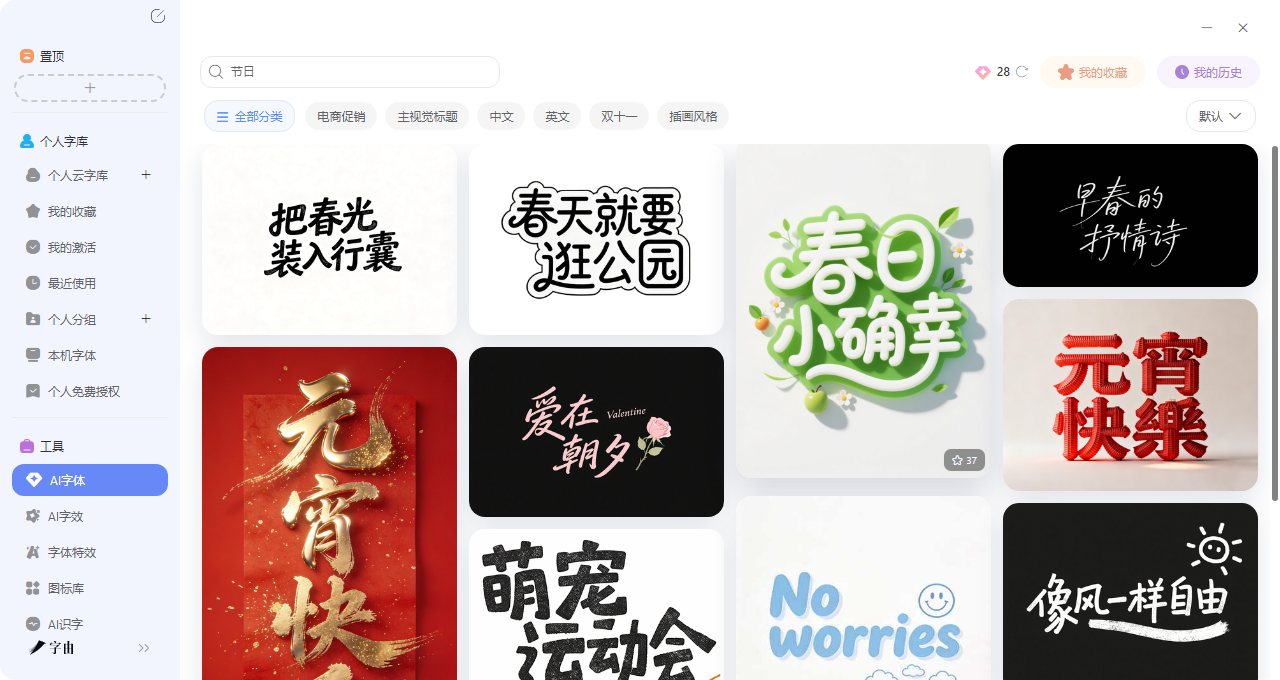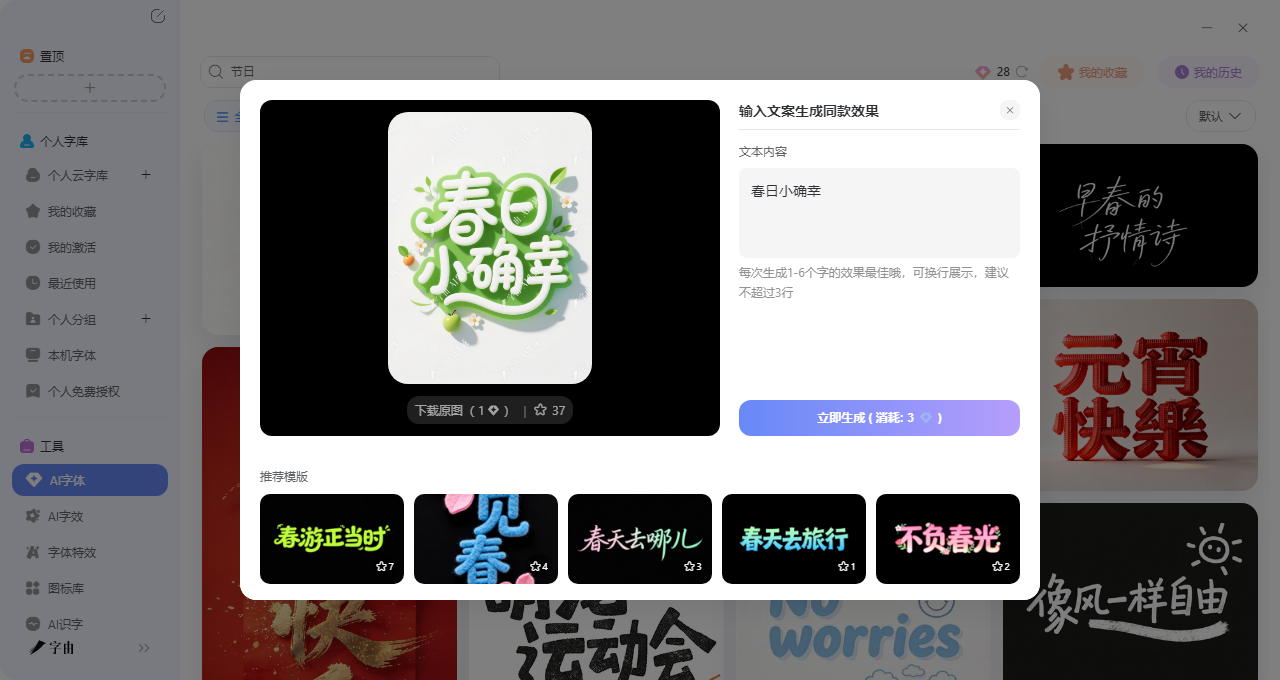
短视频花字自动生成,30秒出效果,剪辑效率翻倍
现在短视频可谓是深入到了我们生活的方方面面,但是所有的优秀的短视频背后肯定都离不开一位优秀的剪辑和封面设计师,温馨的画面加上手写感的文字,酷炫的转场闪过带特效的标题……这些花字就像视频的“弹幕”,能够把情绪和重点精准地带给观众。如果你要问我怎么才能快速地做出一个优秀的短视频花字呢?那我会告诉你只需要在短视频花字自动生成工具里输入文字、选个风格,一键就能生成带特效的动效花字。今天我就筛选了4 个亲测好用的工具,从国产神器字由到国外专业平台,每个都能帮你快速搞定花字。需要的直接收藏,以后做视频不用再愁花字。
你有没有发现,那些爆款短视频里的花字,往往不只是单纯的文字,而是带着效果的艺术字——要么是弹跳入场,要么是渐隐渐显,要么是抖动闪烁。这种效果以前只能在剪辑软件里一帧一帧地做,现在字由的AI字体功能直接把它们做成了模板。更关键的是,你不需要懂动画,也不需要调参数,选个模板,填上文字,点一下,就能拿到带特效的动态花字。接下来我会详细说明如何制作:
第一步:进入AI字体页面后,在搜索框里输入“春日”“节日”“生活”“动态”等关键词,系统会自动筛选出所有适合做花字的模板。
第二步:选一个喜欢的花字模板,下面是推荐的一些模板样式:
- 文艺清新类:“春日”“把春光装入行囊”这种,适合vlog、旅行
- 活泼可爱类:“春天就要逛公园”“萌宠”这种,适合亲子、萌宠、美食
- 洒脱自由类:“像风一样自由”这种,适合运动、公路旅行
- 幸福治愈类:“小确幸”“快樂”这种,适合日常记录、情感短片
每个模板都有预览图,你可以先看效果再决定,点进去还能看到更多细节。选一个和你的视频风格搭的,如果拿不准,可以多试几个。
第三步:点击选中的模板,进入编辑页面。在输入框里填你想生成的花字内容,比如“春日限定”“周末愉快”“今日份快乐”。注意:最好和模板的字数保持一致。
第四步:确认文案后,点“立即生成”,等20-30秒左右就能拿到图。下载时有两个选项:带背景的可以直接用,透明背景的更方便后期排版。直接保存PNG格式,就能拖进剪映、PR等剪辑软件里直接叠加使用。
但是其实字由的AI模板库要比你想象得丰富得多,它不是只有“花字”这个分类,你在“春日”“节日”“生活”里翻到的模板,稍微改一下文案和配色,都能变成你视频里的花字。下面我也会推荐一些我比较喜欢的:
- “春日”:这个模板是温柔的手写风格,字体轻盈,带着春天特有的清新感。文字像是被春风轻轻吹入画面,适合做vlog的开场、旅行记录的情绪标题。配上淡粉或浅绿的背景,治愈感拉满。
- “春天就要逛公园”:这个模板是活泼的卡通风格,字体圆润,带着一种雀跃的节奏。适合做亲子vlog、周末探店、或者任何轻松愉快的视频。文字可以配合公园、草地、风筝的画面,让人看了就想出门。
- “萌宠”:这个模板是可爱的圆体,字体软萌,带着动物耳朵的小装饰。适合做宠物视频的标题。
2、TypeType
TypeType 是一个专业的字体设计公司,它专门有一个“Video Fonts”分类。它推荐了多款适合视频使用的字体,每款都强调在多场景下的可读性和表现力:
- TT Commons Pro:104种字重,从细到粗,还有对应的斜体。这款无衬线体干净现代,适合做视频里的正文字幕、说明文字,或者品牌名。
- TT Norms Pro Serif:24种字重,是经典衬线体,适合做文艺类、访谈类视频的标题,显得有质感。
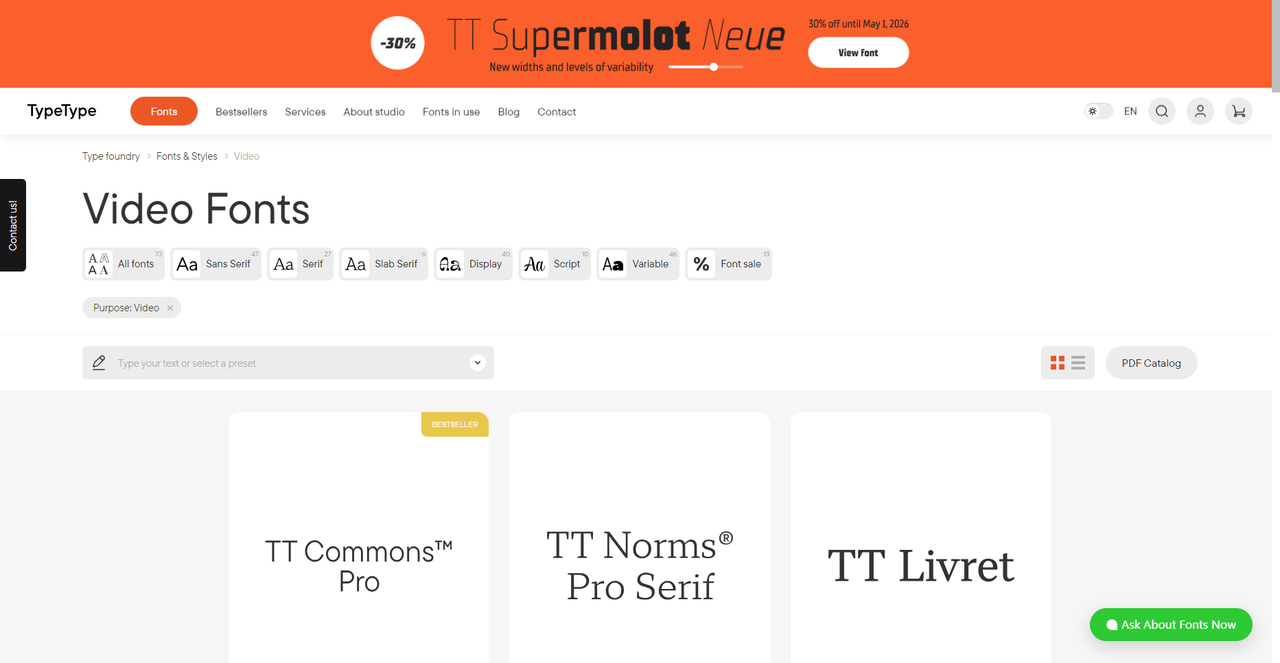
3、Envato Elements
Envato Elements 是一个设计资源平台,它的“Video Fonts”分类收录了大量适合视频使用的字体。从截图看,它推荐了多款热门字体,每款都有详细的风格标签和预览。这些字体很多包含在Envato Elements的订阅中,可以无限次下载使用。如果你需要大量视频资源,这里是个宝藏库。
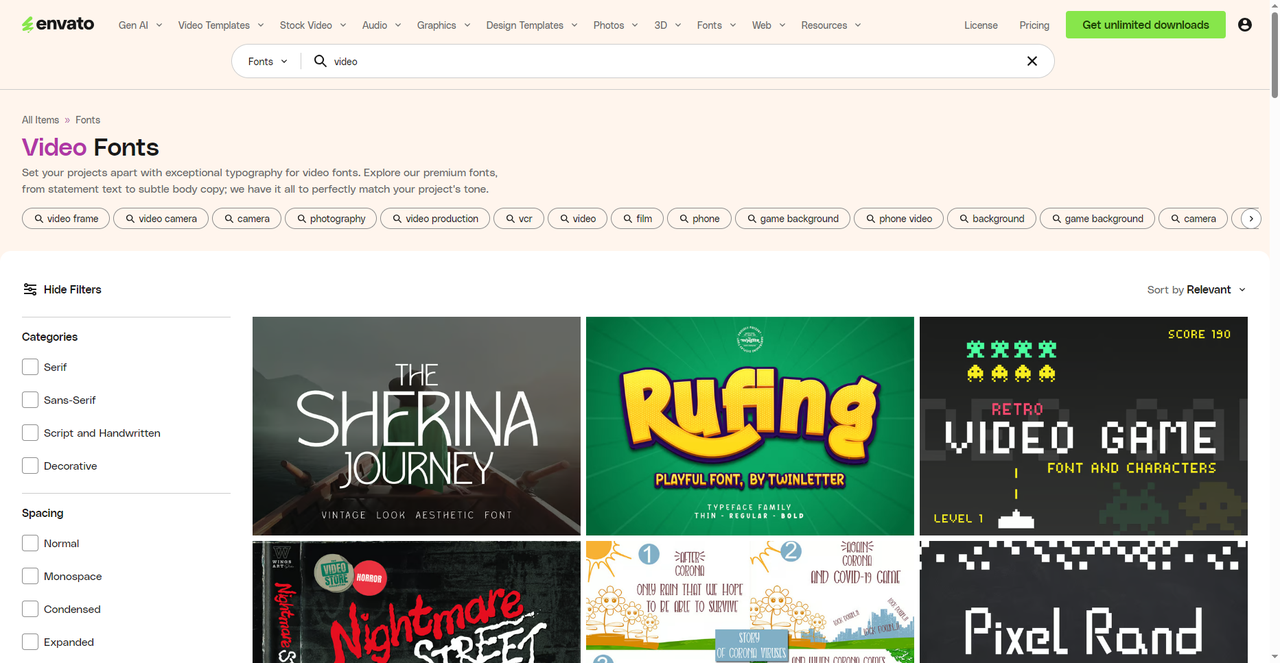
4、Adobe Fonts – Video 系列字体
Adobe Fonts 是Adobe的字体库,它的“Video”系列字体专为视频设计。它展示了一款名为 Video 的字体家族,由Patrick Griffin设计,来自Canada Type。这款字体包含10种字重,从Light到Bold,覆盖了视频中可能用到的各种场景。
- Video Light:纤细优雅,适合做精致的字幕或注释。
- Video Regular:正常字重,适合做正文花字。
- Video Medium:适中字重,适合做次级标题。
- Video SemiBold:较粗,适合做强调性花字。
这套字体线条干净,可读性高,非常适合视频中的动态文字。如果你是Adobe Creative Cloud用户,可以直接同步到PS、PR、AE中使用,无缝集成,非常方便。